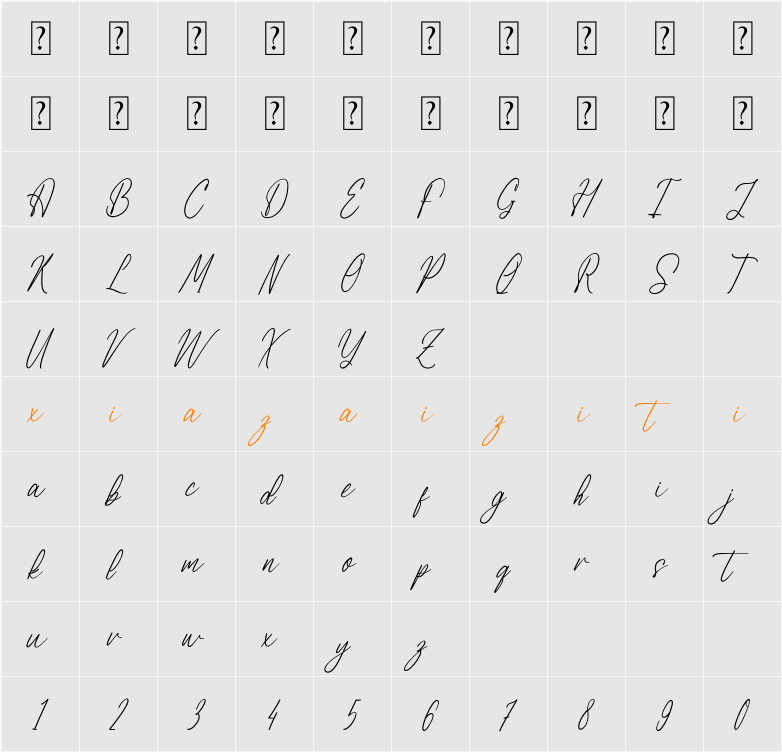
Yustinja
Yustinja,这款字体结构工整、笔画清晰,兼顾美观与易读性,适用于标题、正文、海报、包装、LOGO 等多种场景。字形优雅稳定,风格百搭耐看,适配日常排版与创意设计,让文字呈现更舒适、更具质感。Yustinja一笔一画,皆是细节,以均衡的比例、流畅的线条打造舒适视觉体验,字形端正大气,风格简约现代。无论是商业设计、品牌宣传还是日常排版,都能轻松驾驭,让文字更有格调与力量。Yustinja字体下载。
• 制造商: Letterena Studios
• 设计师: Heru Utama Putra